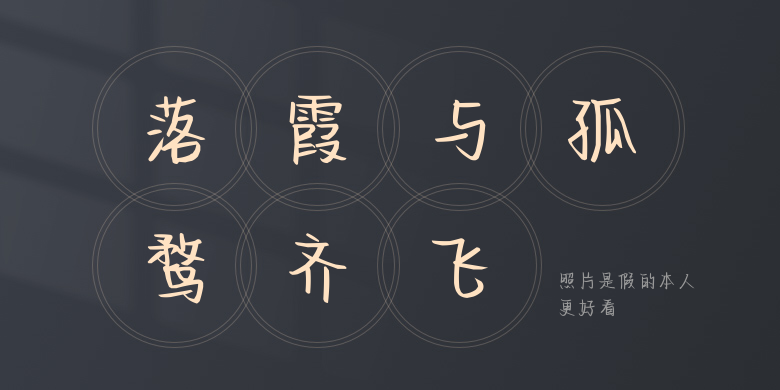
照片是假的本人更好看
照片是假的本人更好看,这款字体结构工整、笔画清晰,兼顾美观与易读性,适用于标题、正文、海报、包装、LOGO 等多种场景。字形优雅稳定,风格百搭耐看,适配日常排版与创意设计,让文字呈现更舒适、更具质感。照片是假的本人更好看一笔一画,皆是细节,以均衡的比例、流畅的线条打造舒适视觉体验,字形端正大气,风格简约现代。无论是商业设计、品牌宣传还是日常排版,都能轻松驾驭,让文字更有格调与力量。照片是假的本人更好看字体下载。